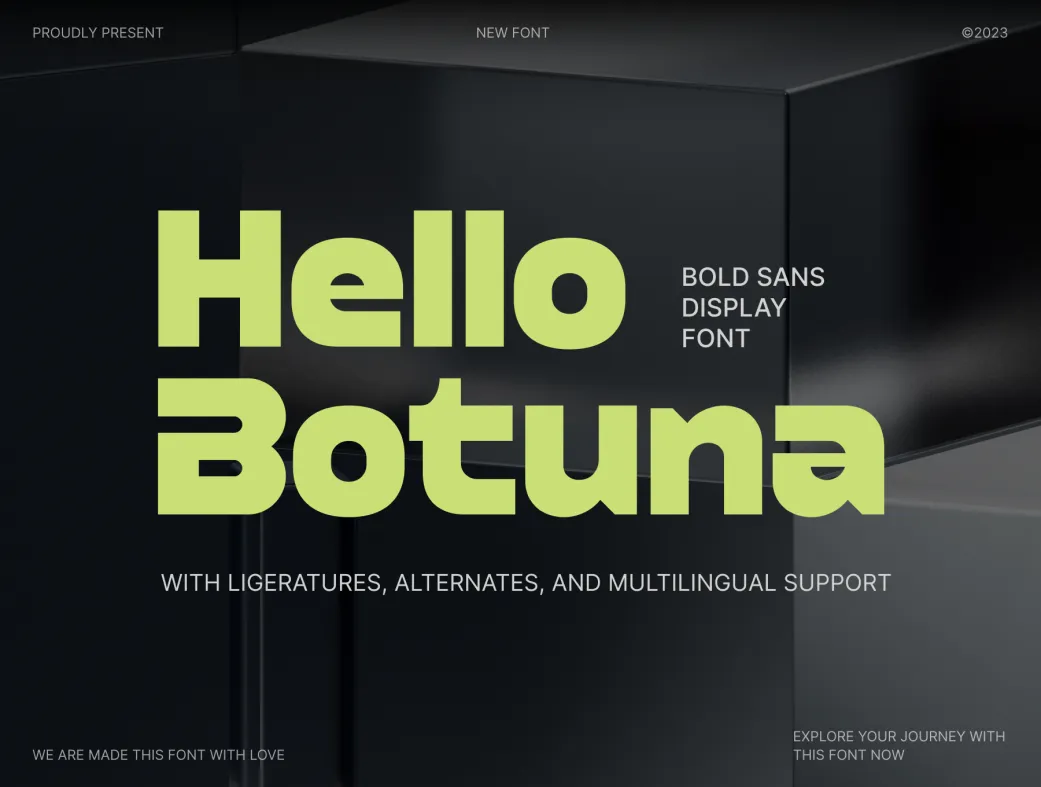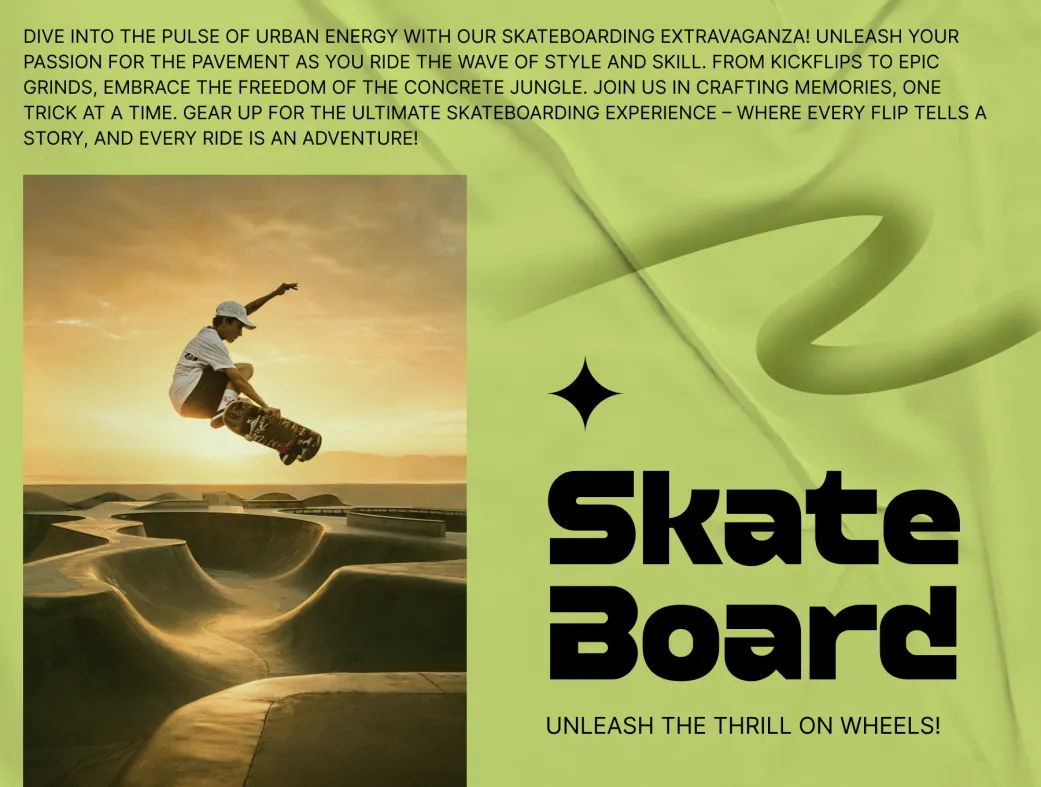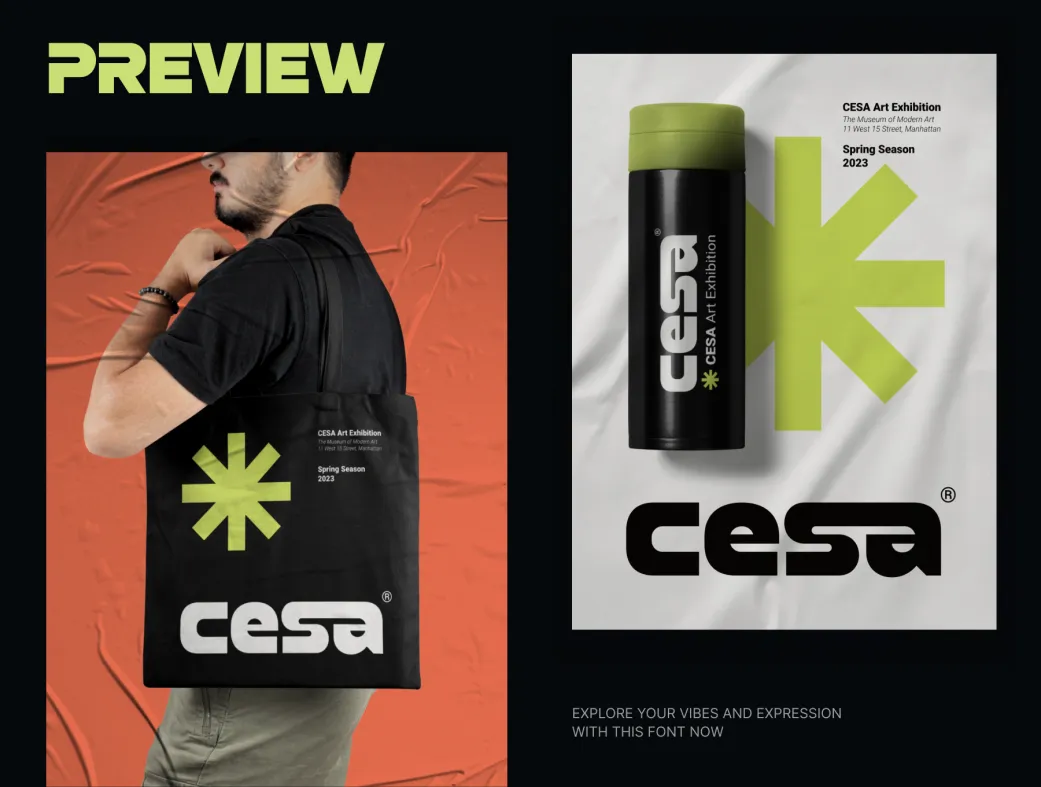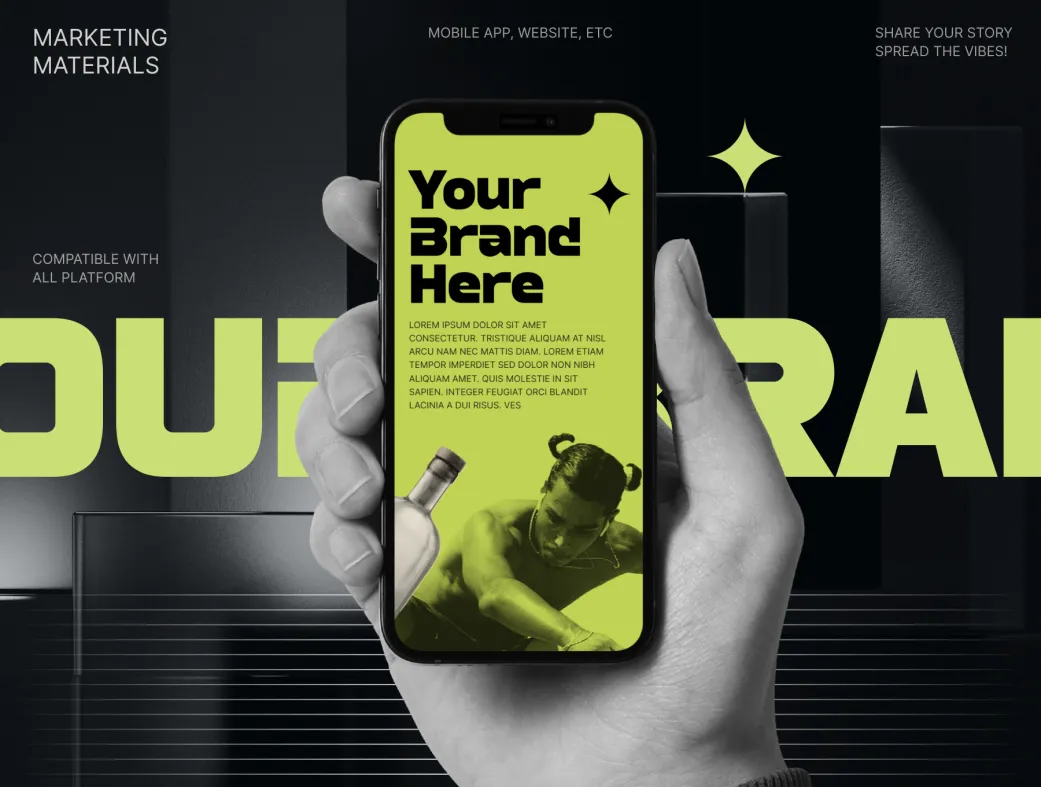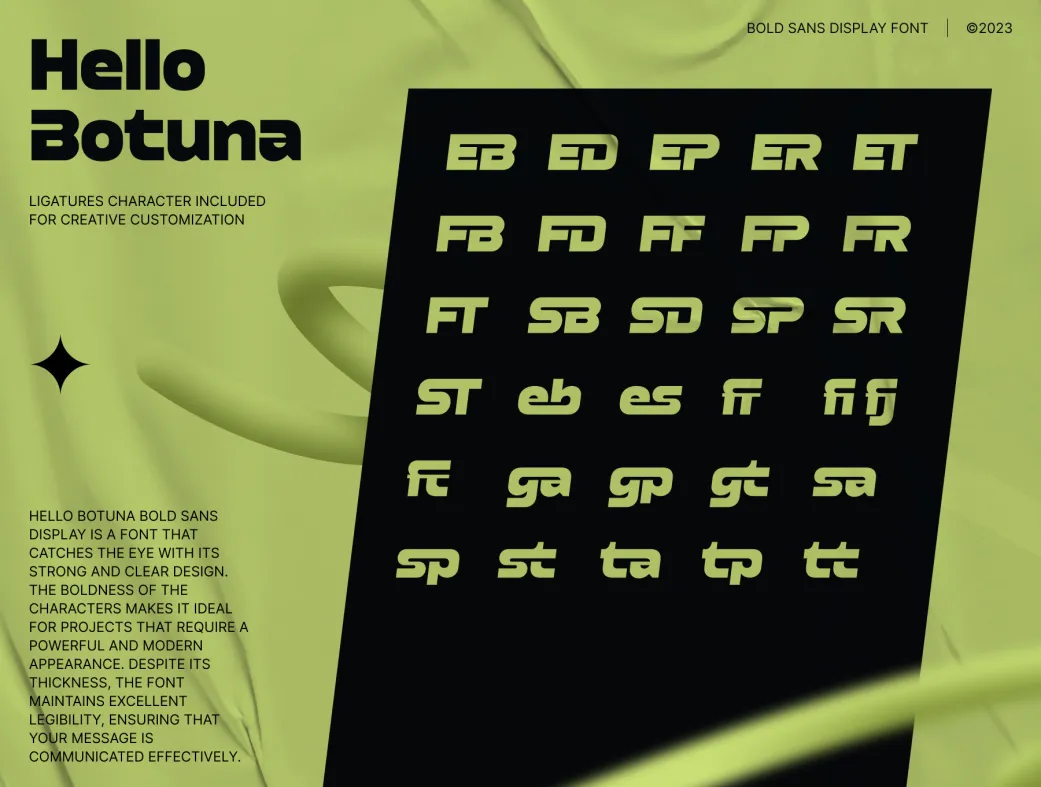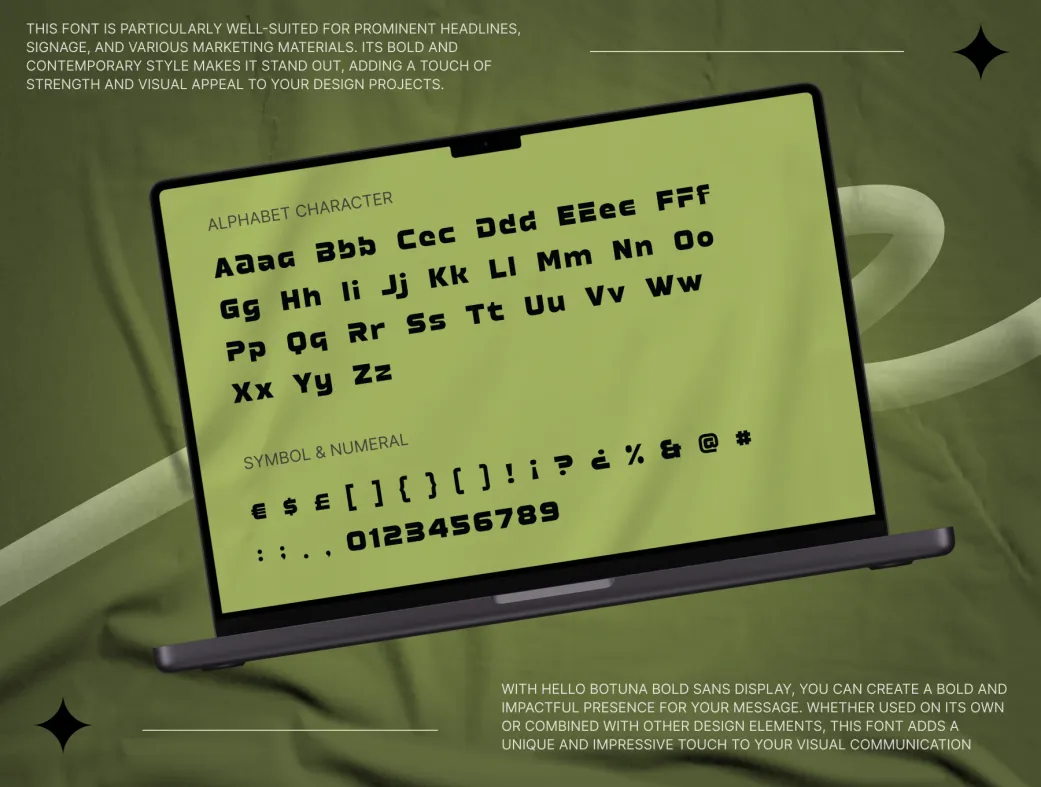
فونت نمایش مدرن و برجسته هلو بوتونا | Hello Botuna
آیا به دنبال فونتی مدرن و جسور هستید؟ هلو بوتونا، انتخابی ایده‌آل برای طراحی‌های تأثیرگذار!
Hello Botuna - Bold Sans Display Font
فونت نمایش مدرن و برجسته هلو بوتونا | Hello Botuna
معرفی محصول:
فونت نمایش مدرن و برجسته هلو بوتونا یک فونت سانس‌سریف جسور است که با طراحی مدرن و جذابیت همیشگی خود، توجه هر بیننده‌ای را جلب می‌کند. این فونت با دقت و توجه به جزئیات ساخته شده و با خطوط تمیز و برجسته‌اش، برای پروژه‌هایی که به تأثیر بصری قوی نیاز دارند، ایده‌آل است. چه در تیترها، لوگوها یا مواد تبلیغاتی، هلو بوتونا بهترین انتخاب برای شماست.
ویژگی‌ها و مزایا:
فونت هلو بوتونا با طراحی جسورانه‌اش، علاوه بر زیبایی بصری، ظاهری متعادل و ظریف دارد که آن را برای استفاده در طیف وسیعی از برنامه‌های طراحی مناسب می‌سازد. کاراکترهای متمایز و خوانای این فونت، اطمینان می‌دهد که پیام شما با وضوح و سبک خاصی منتقل می‌شود. به راحتی می‌توانید از آن در طراحی‌های مختلف استفاده کنید و با شخصیت قوی و جذاب آن، پروژه‌های طراحی خود را به سطح بالاتری ارتقا دهید.
این فونت به‌خصوص برای طراحان گرافیک و برندها که به دنبال ایجاد تأثیر بصری قوی و ماندگار هستند، مناسب است. هلو بوتونا می‌تواند به عنوان یک عنصر کلیدی در هویت بصری برند شما عمل کند و بر جذابیت کلی پروژه‌های شما بیفزاید.
کاربردها و نکات استفاده:
• برای کاربران حرفه‌ای: هلو بوتونا گزینه‌ای عالی برای طراحی لوگو، تیترهای و تبلیغات است. می‌توانید به راحتی از آن در طراحی وب‌سایت و پوسترها استفاده کنید.
• برای کاربران مبتدی: این فونت به دلیل سادگی و وضوحش، برای کسانی که به تازگی وارد دنیای طراحی شده‌اند نیز بسیار مناسب است. می‌توانید با استفاده از این فونت، آثار خود را به راحتی زیبا و جذاب کنید.